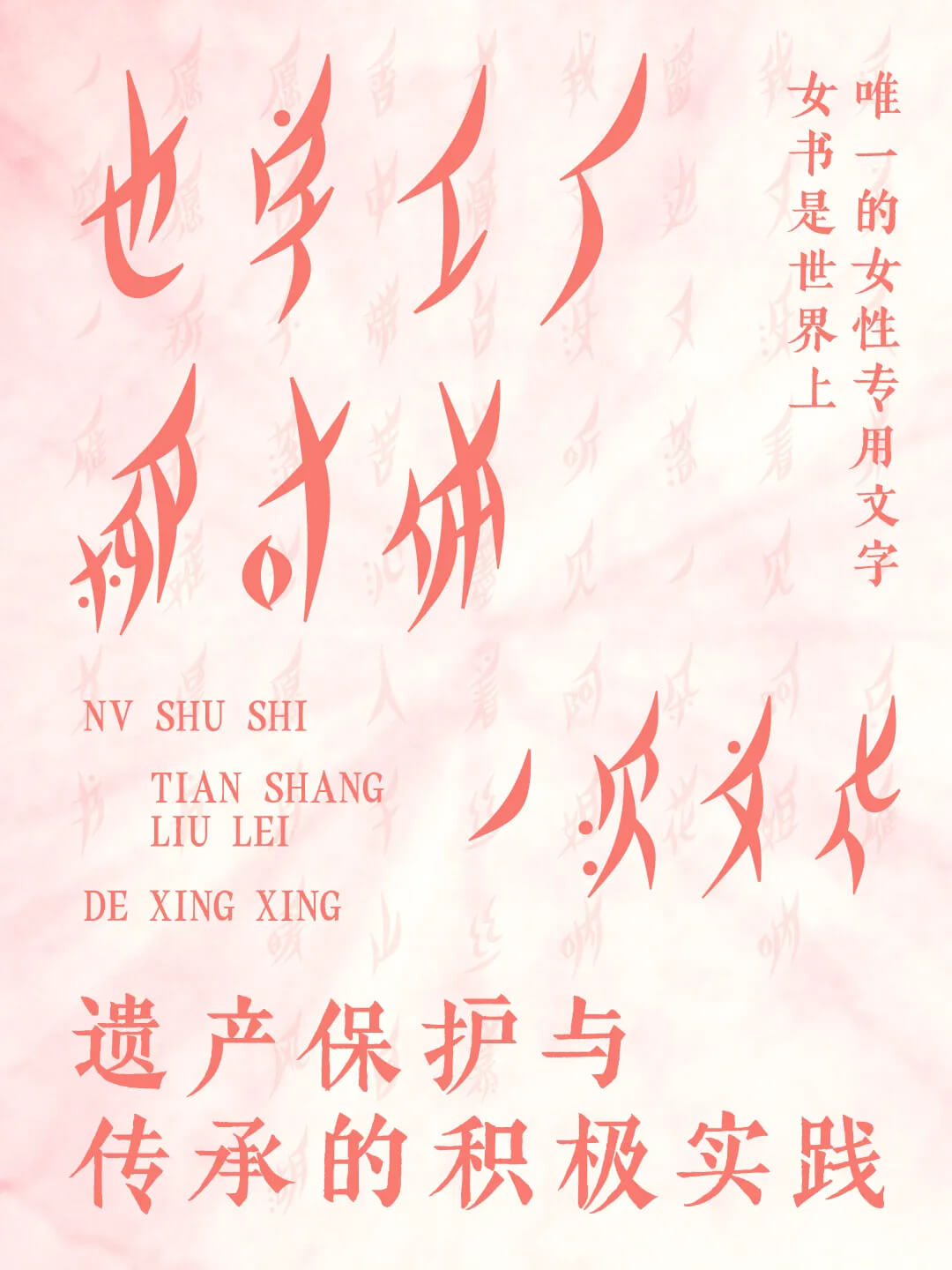
也字工厂柳叶体
在2023年,一次偶然的机会让我们认识了女书文字作为世界上唯一的女性文字,女书成为了中国语言生活中的一个独特现象它象征着一种“阳光文化”赋予了女性话语权同时也是一种文化抗争,犹如一缕阳光为女性生活带来愉悦
也字工厂柳叶体,借封建制度下被受压迫的女性唤醒人们对权益的维护与关注
字型设计上汲取了江永女书的笔画和结构特征呈现出明显的左低右高特点,字型倾斜角度较大字体设计呈左右结构左边部分偏小偏低,更符合江永女书的书写特征
以斜、弧两种笔画为主,还原了江永女书的写法笔画弧度富有弹性,笔形柔和不失洒脱
字体倾斜修长,娟秀清瘦,宛如柳叶,又似月亮在满足汉字造型的同时尽可能还原女书的独特感觉
在保持识别性的前提下,简化竖提、横折钩、竖弯钩等的设计使字体整体更具统一性,更贴近女书的风格在同一个字体中,笔画粗细差别较大,更有手写的轻松感和人文感视觉冲击力大,更容易有记忆点
口的造型虽然女书中这个造型代表的意思不同,但其造型与汉字的口相似所以提取这个造型做汉字版的口,既不影响识别又贴近女书造型
在不影响识别的情况下,对一些字体笔画进行省略同时使用点来替代撇捺造型,既更贴近女书的风格,又增加了创意感
我们支持女书,正是感受到了来自百年前女性独立精神的振荡,站在历史长河的下游,我们凝望着这群伟大女性沉默的搏斗,这份精神直至今日,仍会鼓舞千千万万女性为自己而奋斗。
我们宣传女书,并非只想让她存在于博物馆的玻璃展柜里,让来往观众驻足片刻。我们深知,要让一种文化源远流长,就得让其生活在人群中间女书不仅要“火”起来,更要“活”起来。
女书,是中国古代女性创造的一种仅限于女性之间交流的文字,流传在湖南江永潇水流域,是迄今发现的世界上唯一的女性文字。女书的形成无疑是一种复杂的社会文化现象,但可以发现,在当时”男尊女卑、男主女从”的环境下,女性的声音被压抑,女书的产生就是为了满足女性之间交际的隐蔽需要,反映了当时女性对性别压迫的觉醒和抗争,从喃喃自语走向了更公众的领域。